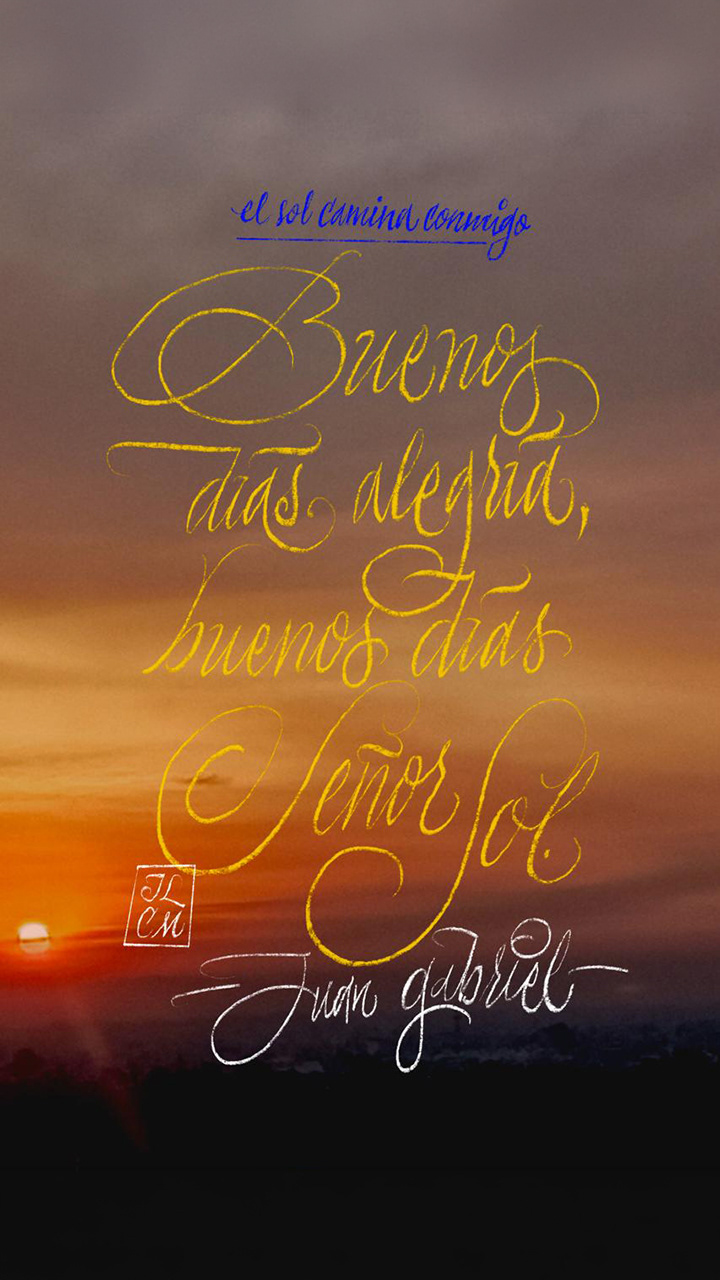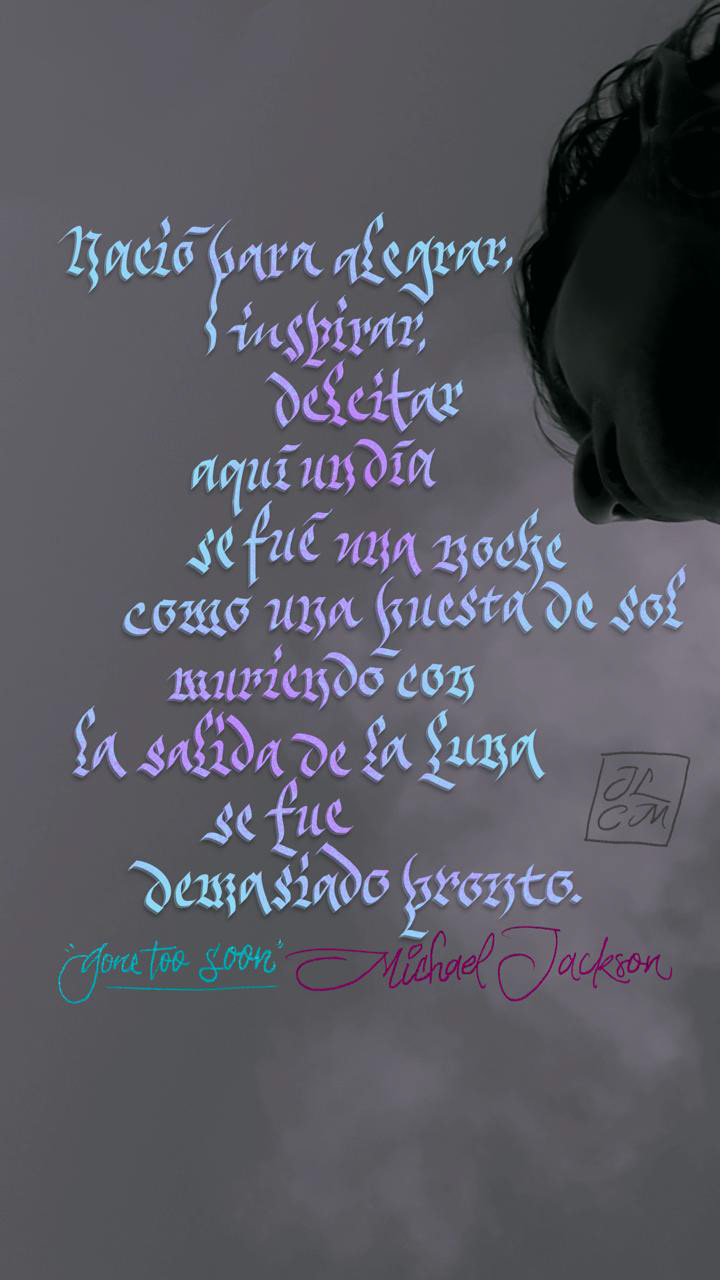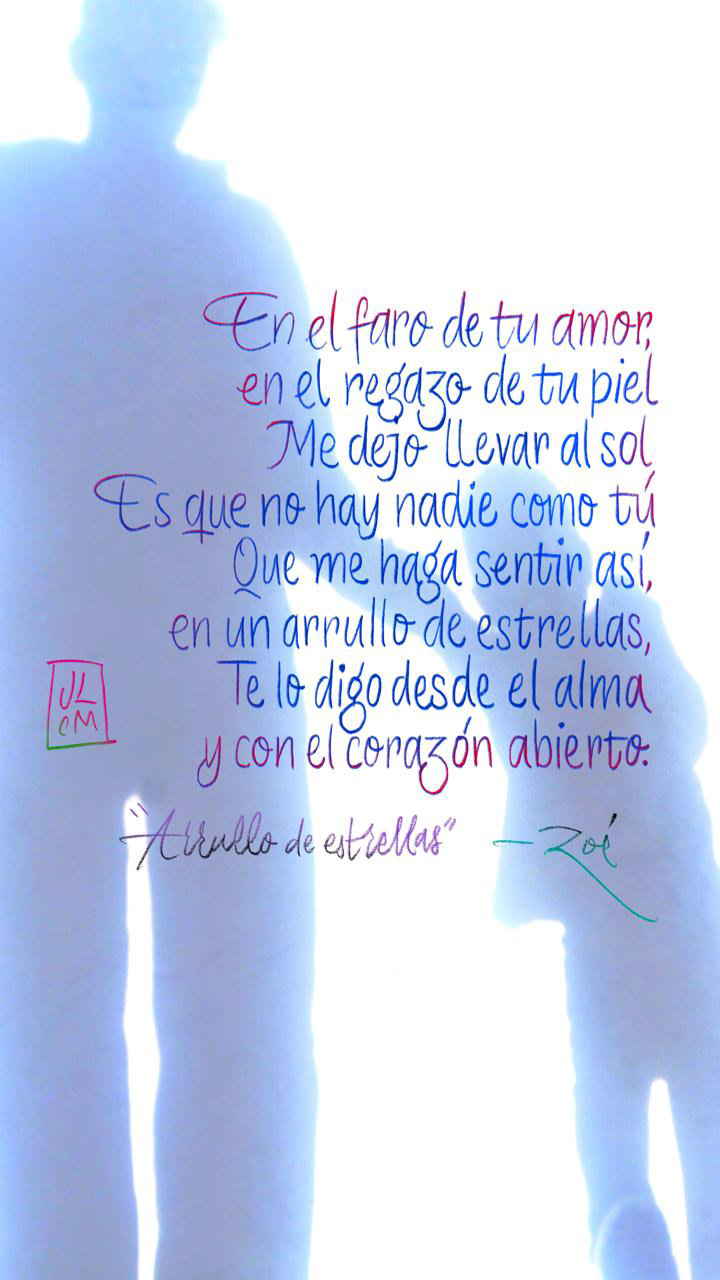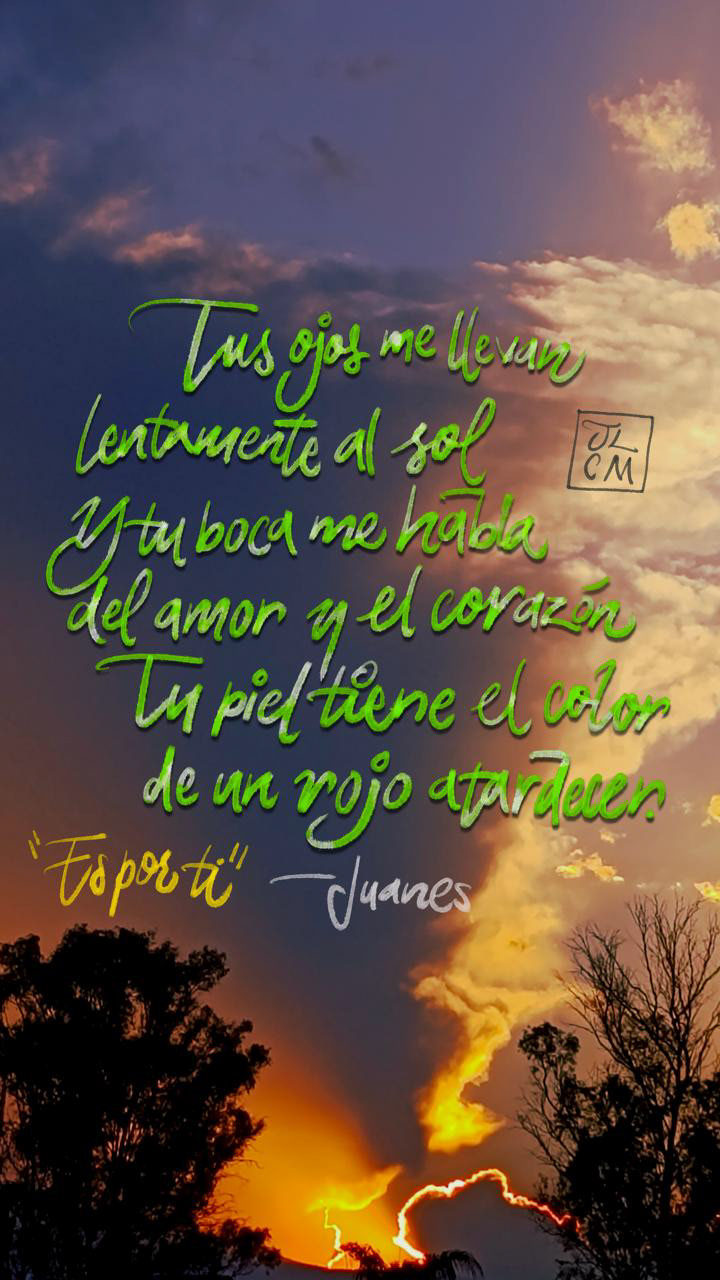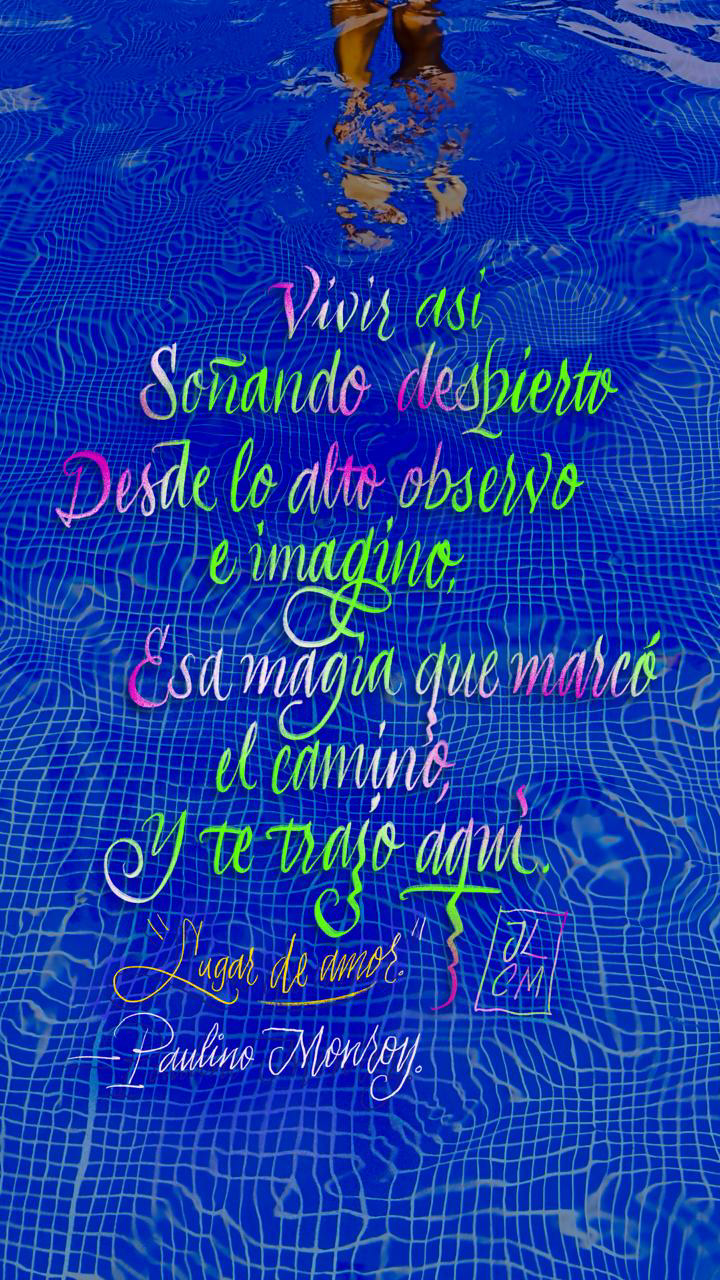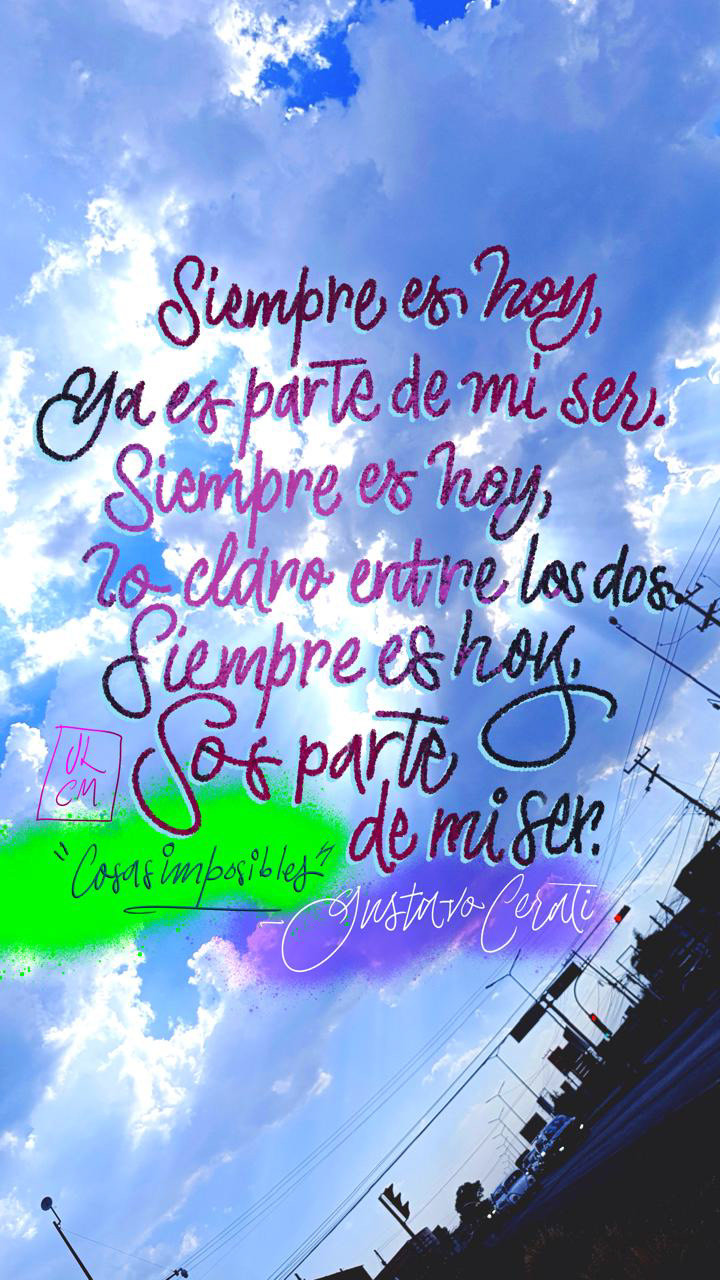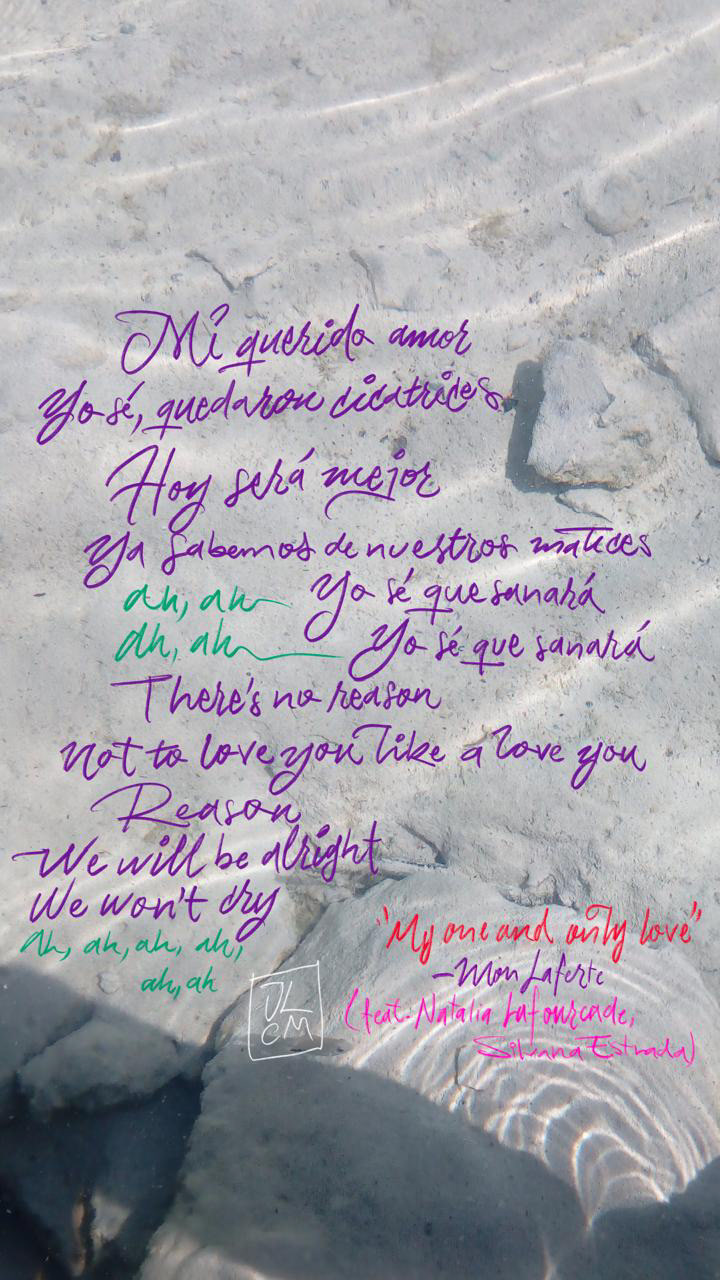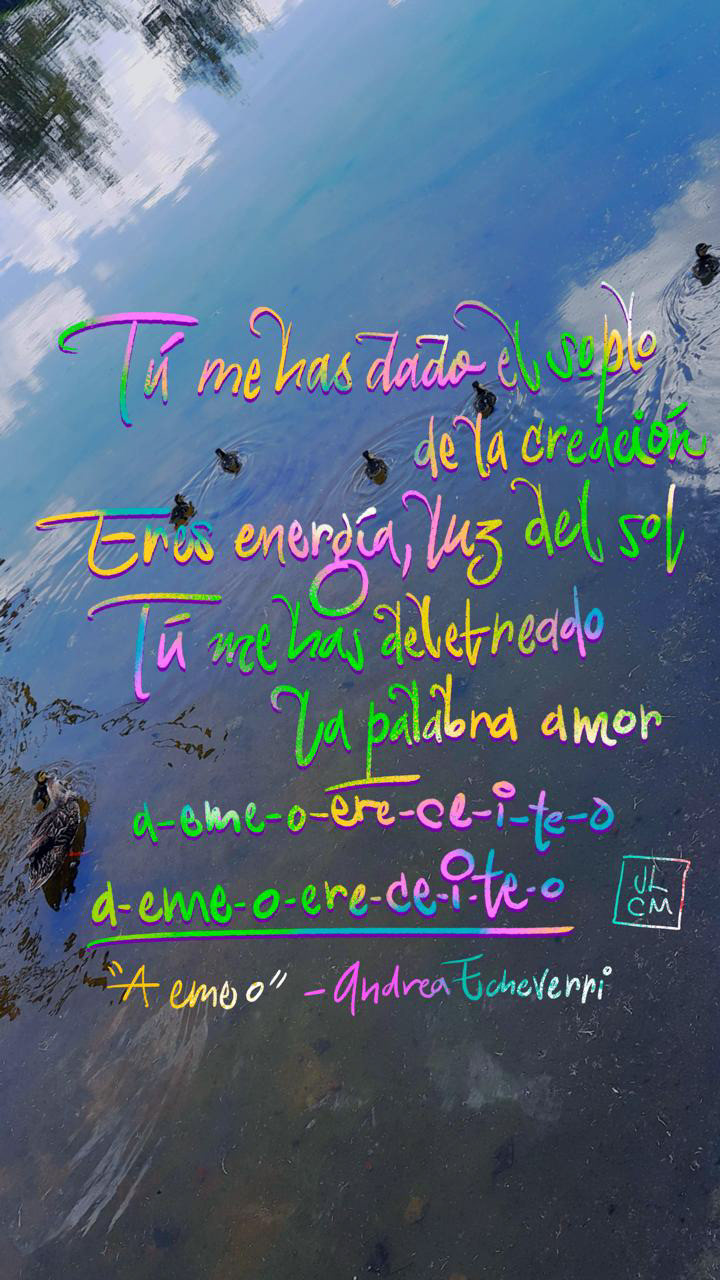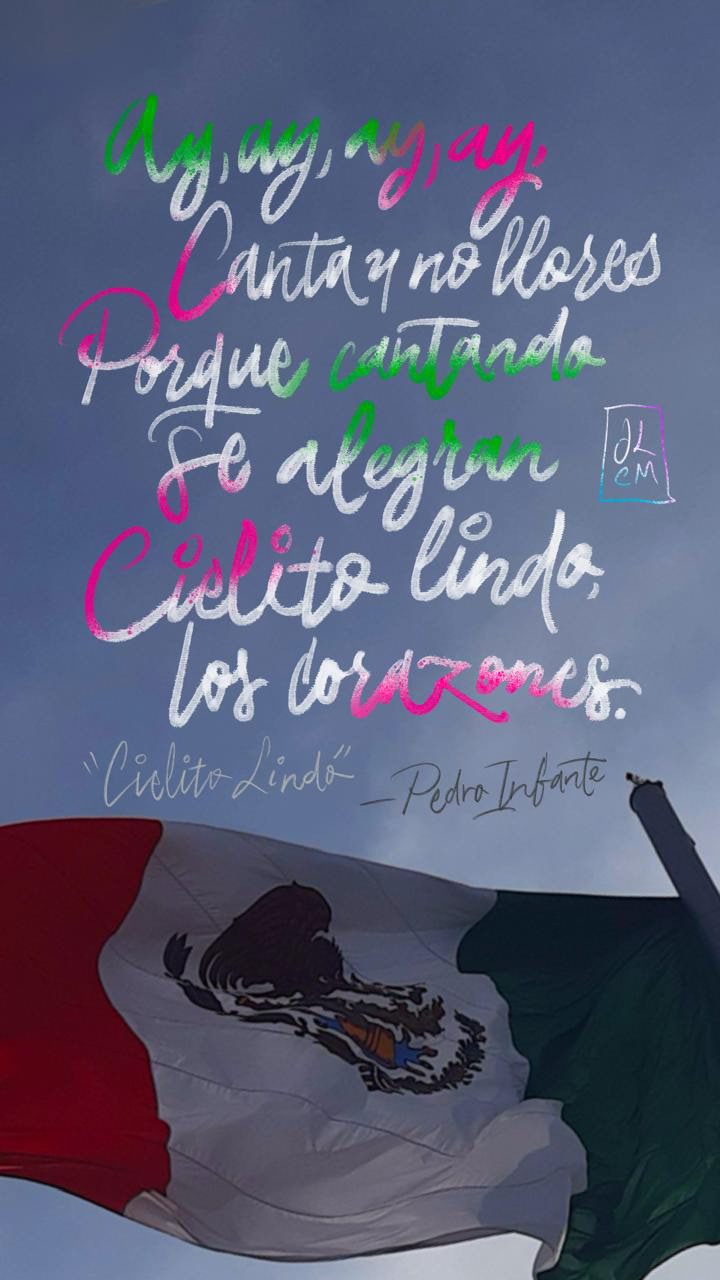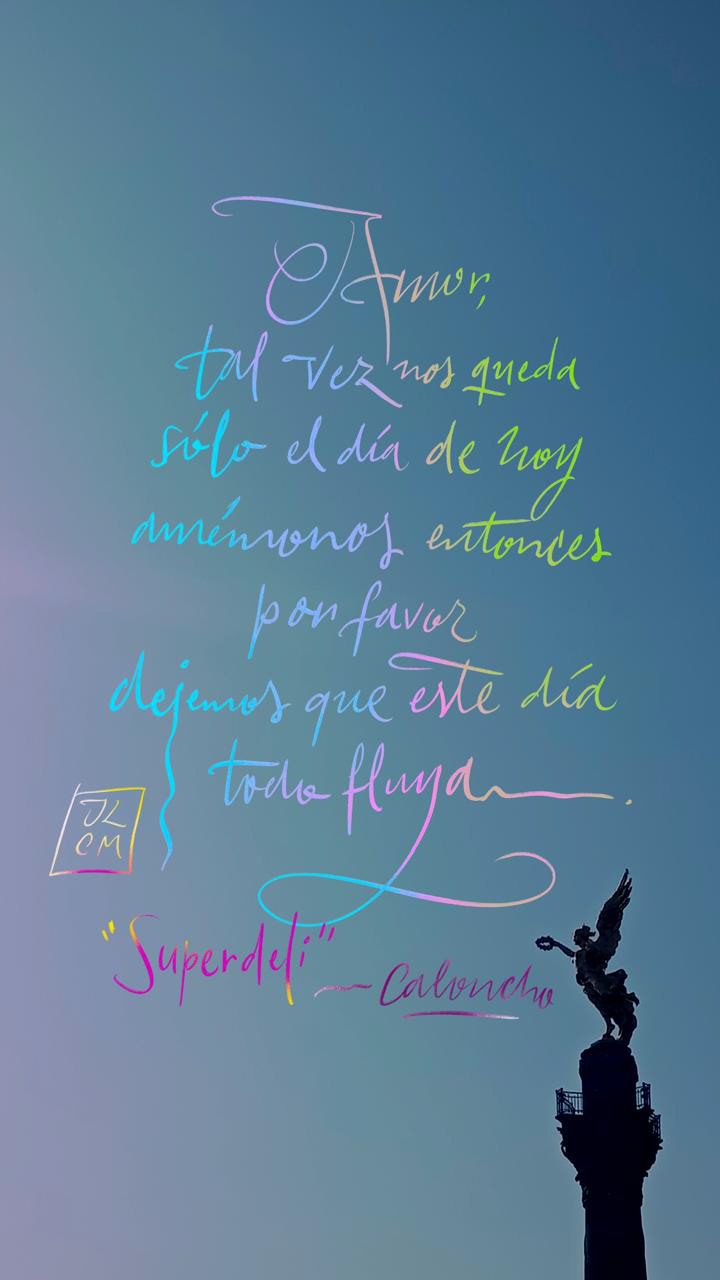
EL SOL CAMINA CONMIGO 6
Sexta parte de "El Sol Camina Conmigo", un proyecto de postales digitales e historias para redes sociales con letras de canciones que me encanta cantar. Esta colección combina composiciones de caligrafía realizadas con Procreate en iPad con fotografías que tomo en diferentes lugares.
Esta colección consta de 24 piezas creadas durante la primavera y el verano de 2026, destinadas principalmente a Facebook e Instagram: El Sol Camina Conmigo